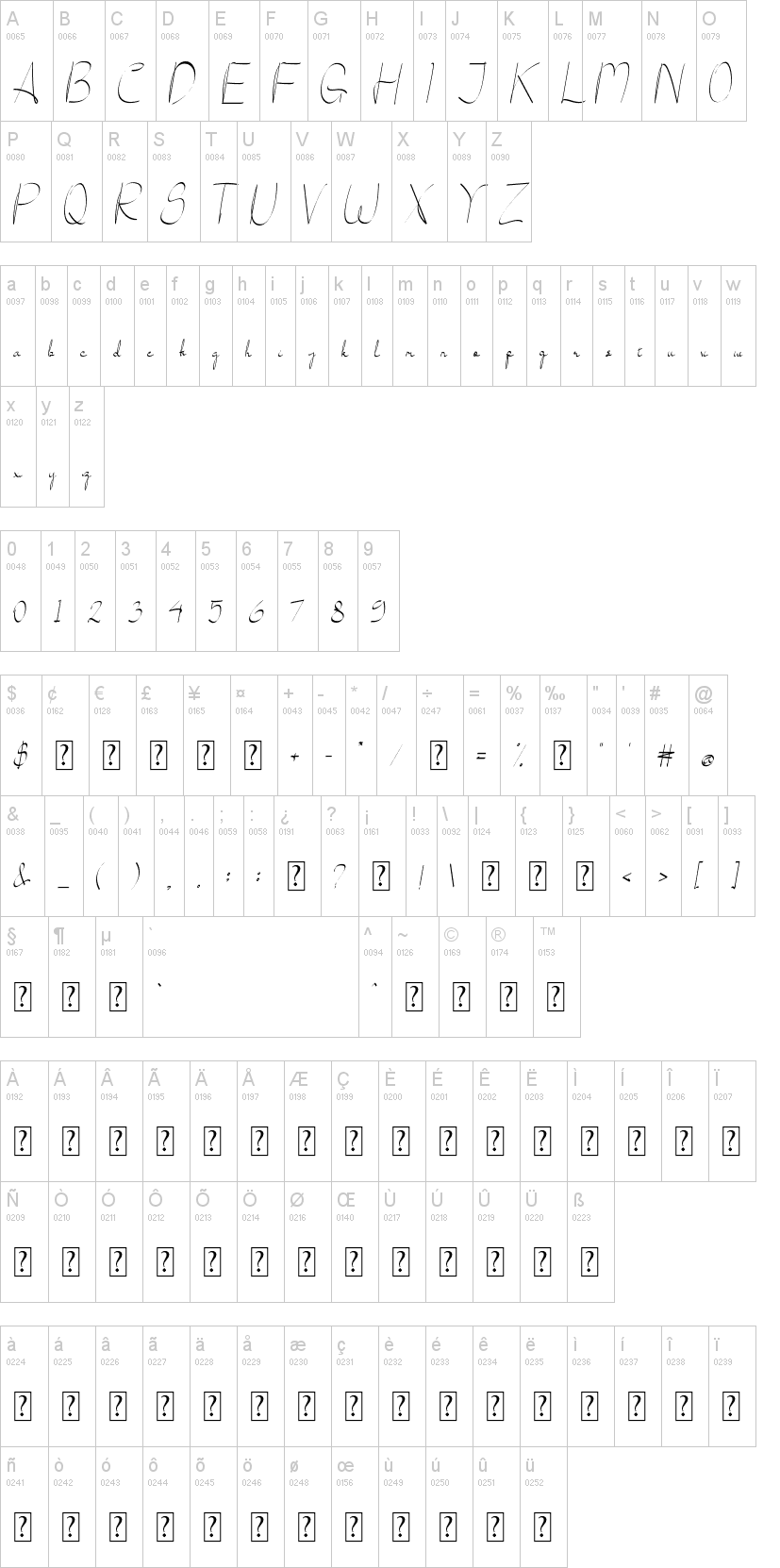
Taylilla
? Taylilla 是一款现代感十足的手写字体,由著名的设计师Taylilla所设计,它具有流畅的曲线和细腻的笔画,让人的字体显得更加精致、优雅。它可以应用于各种设计项目,如海报、标识、标题、书籍封面等,也可以用于网页设计中。Taylilla字体具有独特的风格,可以给你的设计带来活力和新鲜感,让你的设计更加精致而优雅。
Taylilla是一款非常不错的手写艺术字体,具有很好的视觉感,适合于文化类的宣传设计、商业类品牌的广告和产品包装设计以及个性化文字排版等较多场景。
Taylilla字符映射图